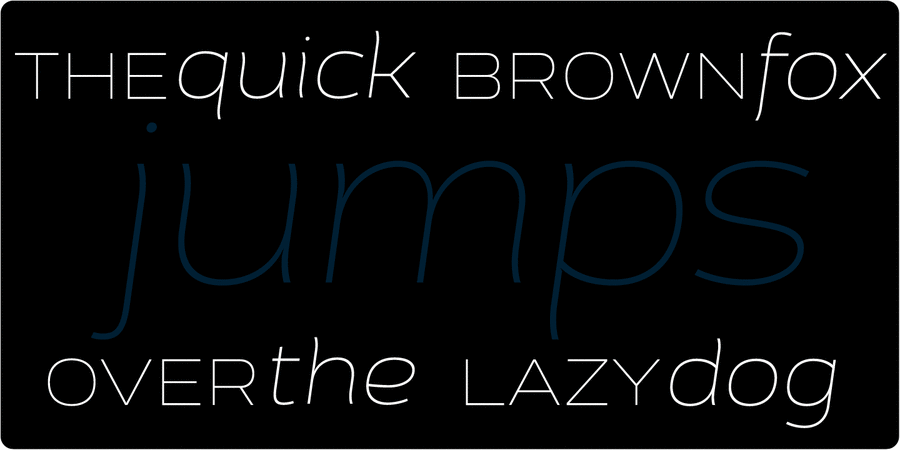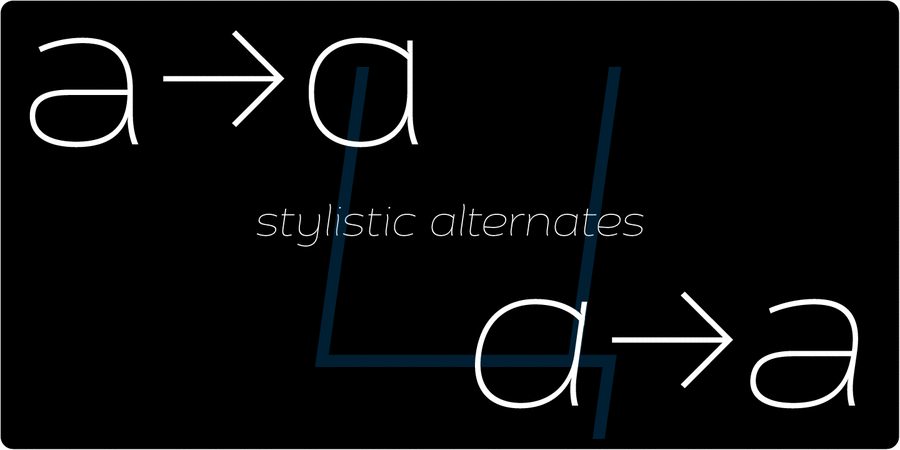
Шрифт Цедра содержит 4 насыщенности и курсивные начертания к ним. Отлично подходит для рекламы, журналов и другой акциденции. Разработан Сергеем Ткаченко в 2010-2013 году.
Асоціації з сімейством шрифтів Cedra 4F WideОсобистість і характер гарнітури:
делікатний, чистий, легкий, прохолодний, свіжий, модний, міський, тонкий, сучасний, лаконічний, вільний, невагомий, прозорий, інтимний, крихкий, ніжний, повітряний, дротяний, зелений, природний, органічний, гнучкий, мирний, добрий, Простий, комфортний, довірчий, доброзичливий, ввічливий, екологічний, стабільний